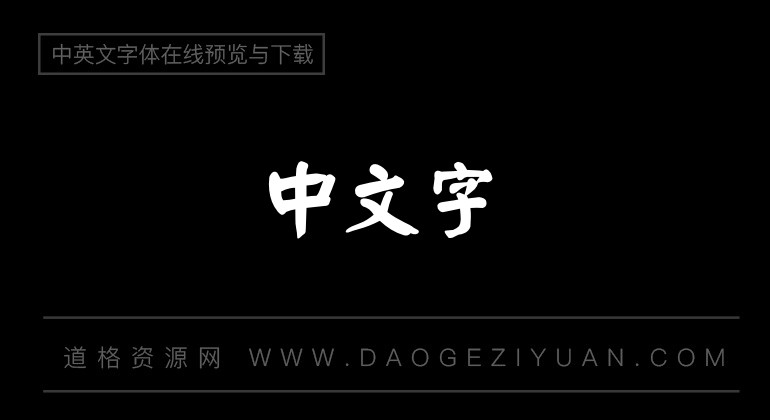
蒙纳繁颜楷
蒙纳繁颜楷(Mona Fancy Kaiti)是一款比较古典的中文字体,它的特点是线条细腻,笔画自然,字形清新,具有极强的视觉冲击力,可以营造出一种清新淡雅的氛围。蒙纳繁颜楷字体也可以用来表达传统文化,给人以古典、深沉、温暖的感觉。
蒙纳繁颜楷是一款非常不错的手写艺术字体,具有很好的视觉感,适合于文化类的宣传设计、商业类品牌的广告和产品包装设计以及个性化文字排版等较多场景。